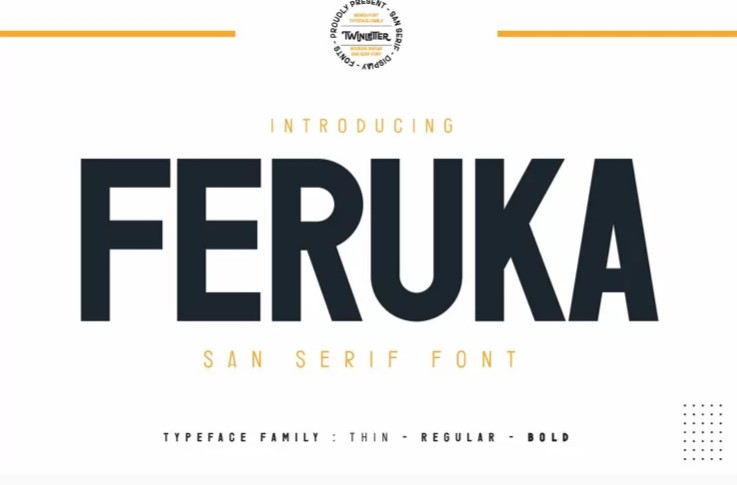
Представляем шрифт Feruka sanserif.
All Capital sans очарователен и доблестен в своем применении, шрифт со смелым стилем и сильным характером, который заставляет ваш дизайн выглядеть смело и дерзко, чтобы передать сообщения потребителям в каждом дизайне, этот шрифт оснащен обычными и жирными тонкими вариациями, чтобы упростить и удовлетворить проектные потребности вас.
Мы разработали этот шрифт семейства San Serif, обратив внимание на сочетание каждой буквы, чтобы создать красивое впечатление и внешний вид, что облегчает удовлетворение ваших потребностей, как формальных, так и неформальных.
Этот шрифт идеально подходит для самых разных дизайнерских проектов, спортивных мероприятий, брендинга, баннеров, плакатов, названий фильмов, продуктов питания и напитков, технологий, цитат, одежды, логотипов и многого другого.
Конечно, с использованием этого шрифта ваши различные дизайнерские проекты будут идеальными и удивительными, потому что этот шрифт поставляется с семейством шрифтов, как для заголовков, так и для субтитров и текста предложений, начните использовать наши шрифты для ваших удивительных проектов.